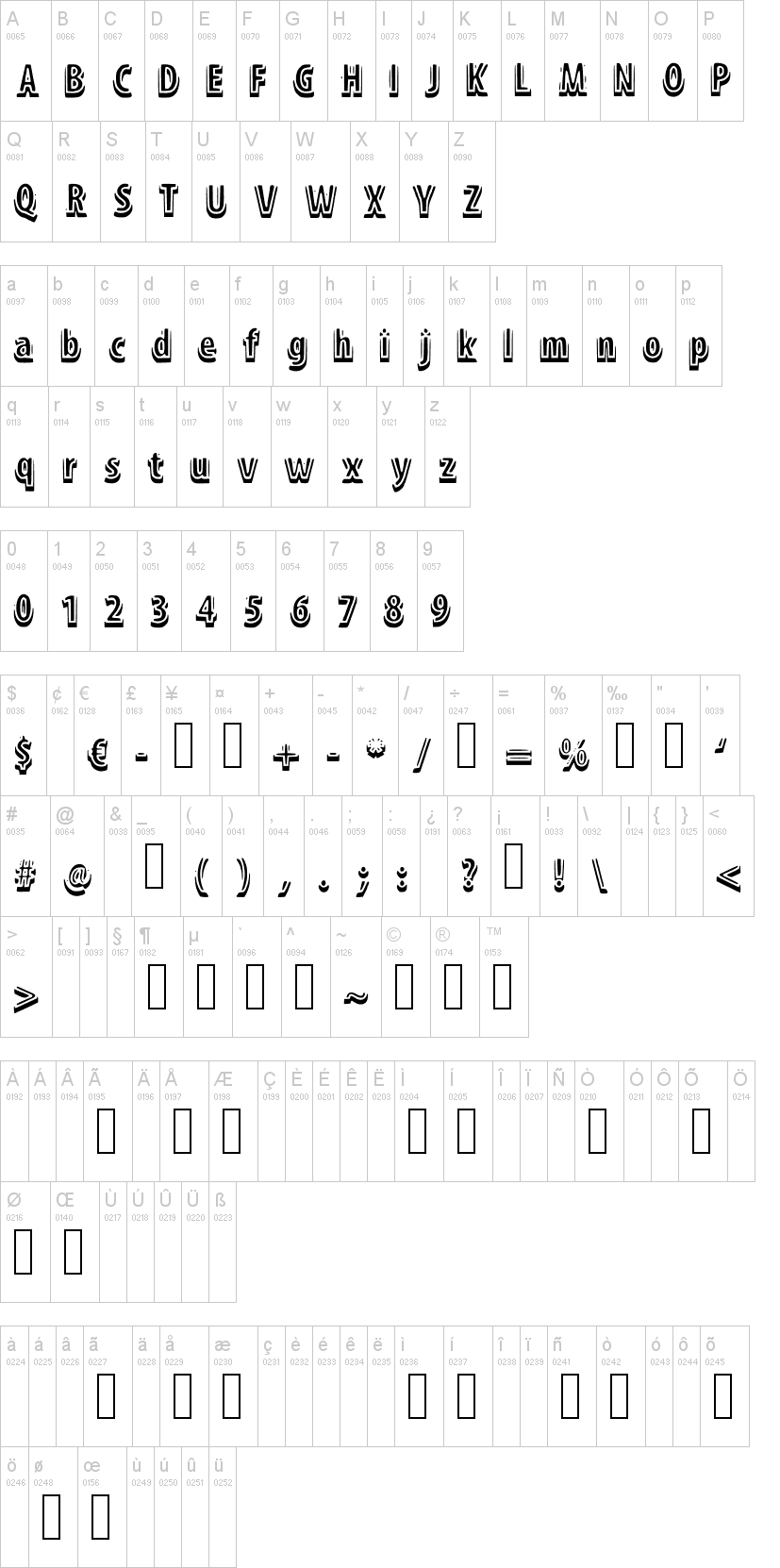
ShadowM
ShadowM 字体是一款新型的字体,它是由 ShadowM 团队开发的一种字体,它专注于提供简洁、精致、灵活的字体设计,以及更加现代化的字体体系。ShadowM 字体可以用于网页、印刷、桌面等多种应用,可以满足不同的设计需求。ShadowM 字体的特点是,它的字形设计简洁,比较现代化,更加灵活,可以满足不同的设计需求,而且字体的渲染效果也比较出色。
ShadowM是一款非常不错的手写艺术字体,具有很好的视觉感,适合于文化类的宣传设计、商业类品牌的广告和产品包装设计以及个性化文字排版等较多场景。